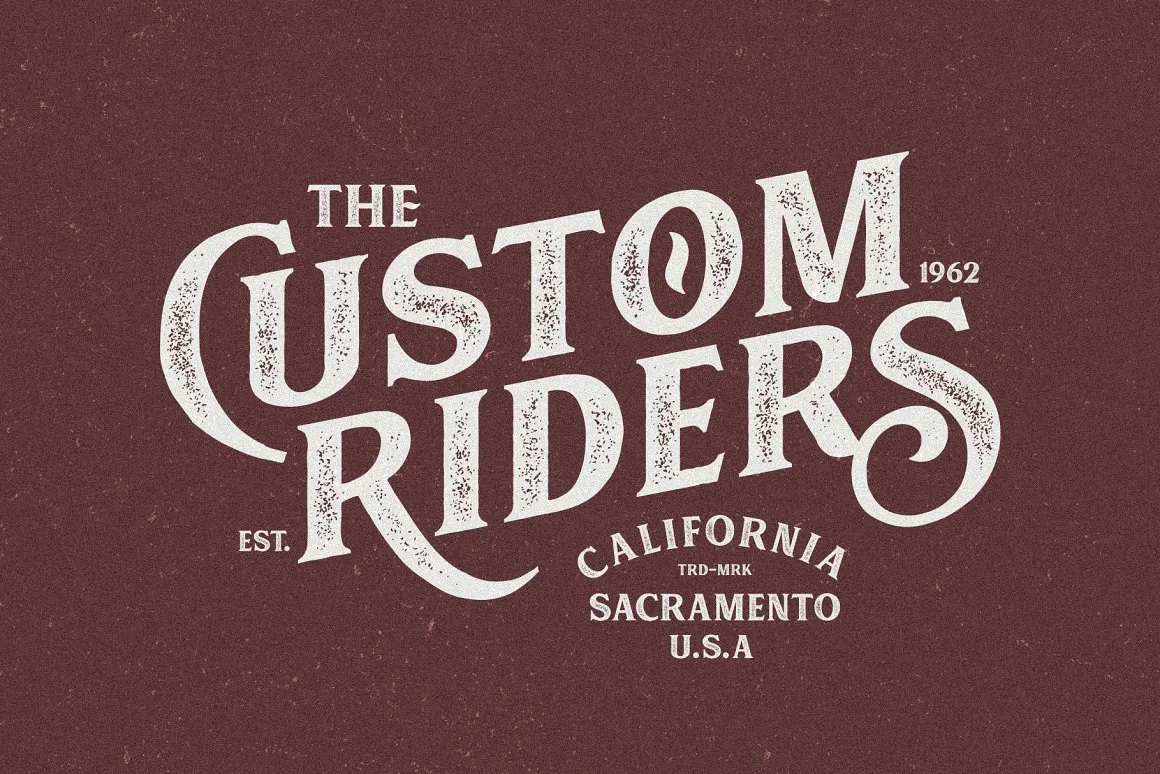
Descubra a sofisticação e elegância da Muara Rough Typeface, uma nova opção criativa para seu próximo projeto visual. Introduzida pelo profissional designer Adil Budianto de Yogyakarta, Indonésia, esta tipografia exibe um sabor clássico que se adapta perfeitamente a diversos formatos. Perfeita tanto para criações visuais como livros, revistas, embalagens e rótulos, quanto para logotipos e identidades de marca, Muara Rough também traz uma versão com letras em maiúsculas, mantendo o estilo distintivo da série Muara. Com mais de 330 caracteres disponíveis, a Muara Rough No.23 inclui alternativas estilísticas, conjuntos estilísticos e variante em estilo swash, proporcionando um grande leque de opções para designers gráficos. Esta fonte oferece uma gama de personalidades únicas que se tornam ótimas escolhas para trabalhos de design, ajudando você a destacar seus projetos visuais. Com sua simplicidade e elegância clássica, a Muara Rough é perfeita para qualquer projeto criativo onde desejar ser notado.